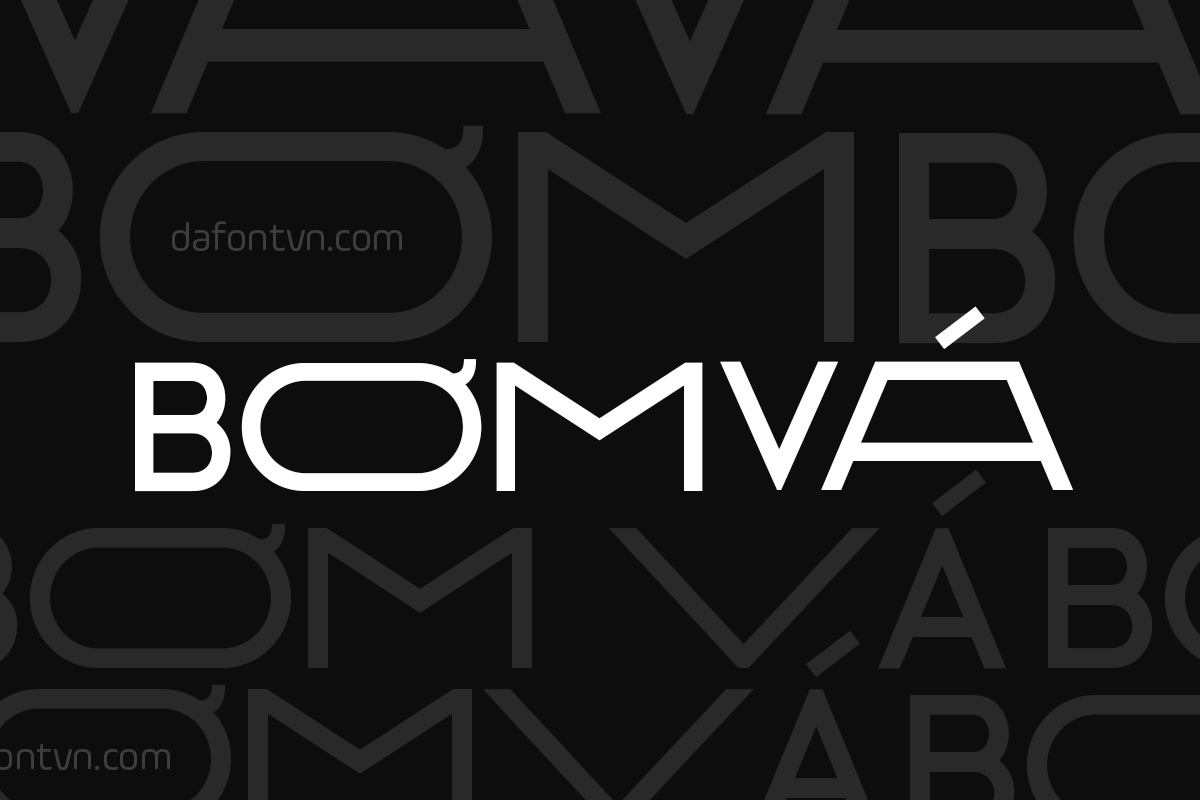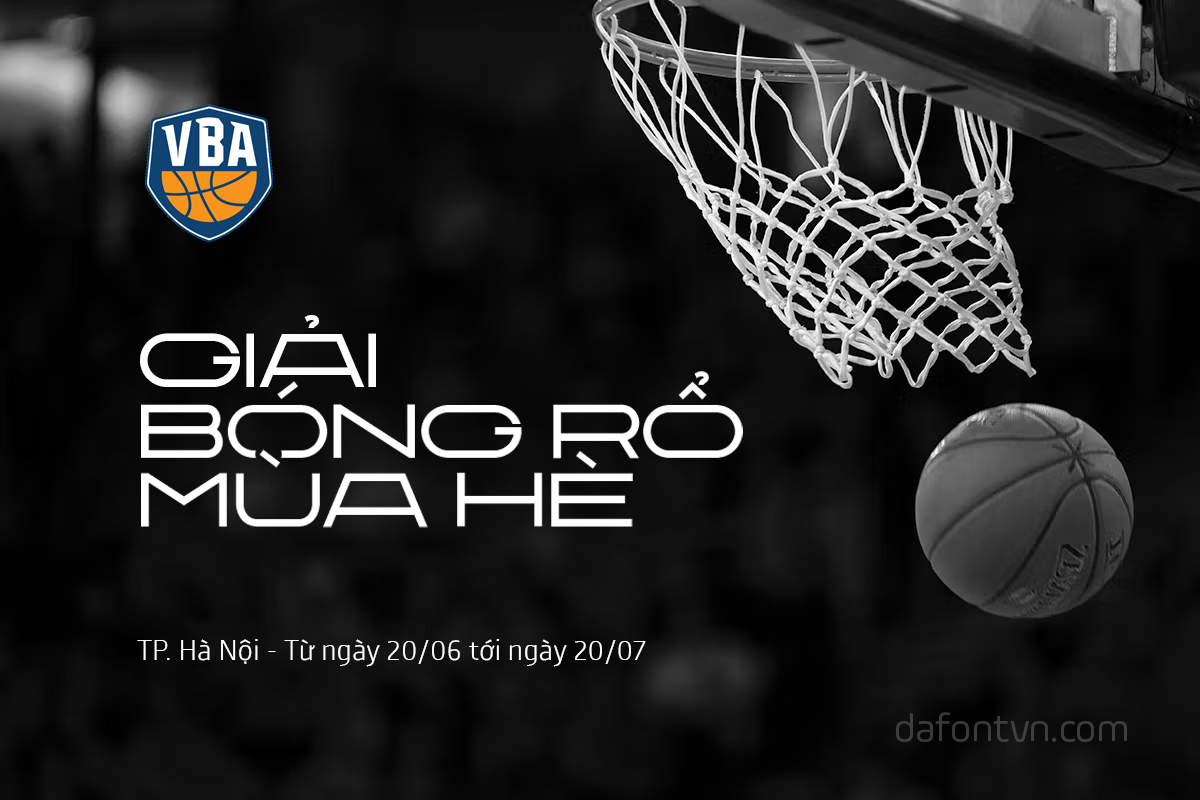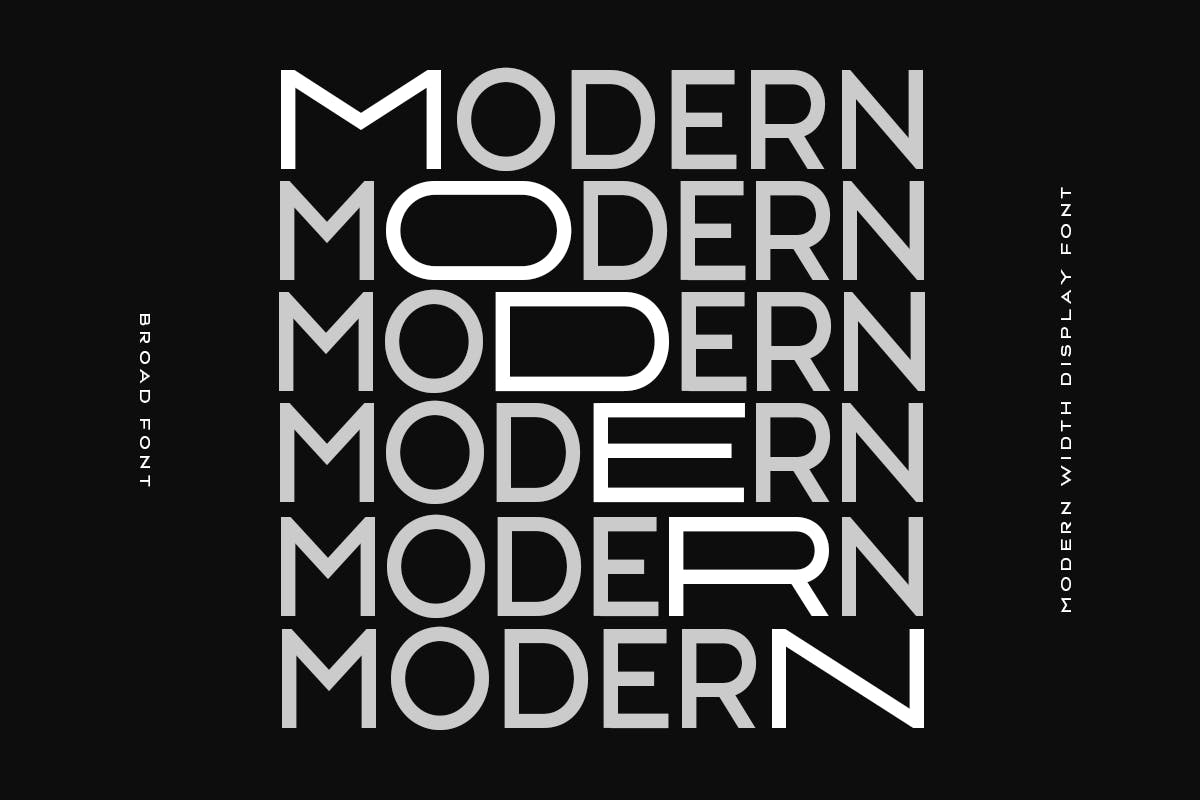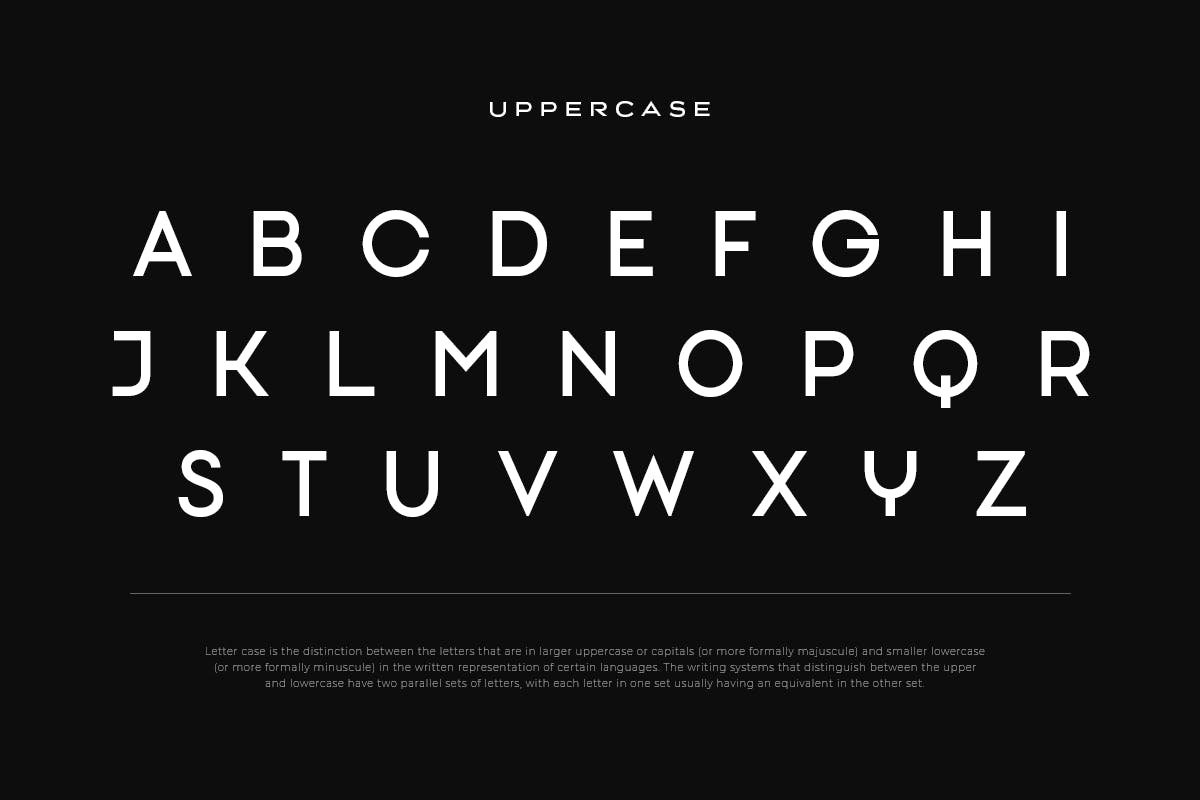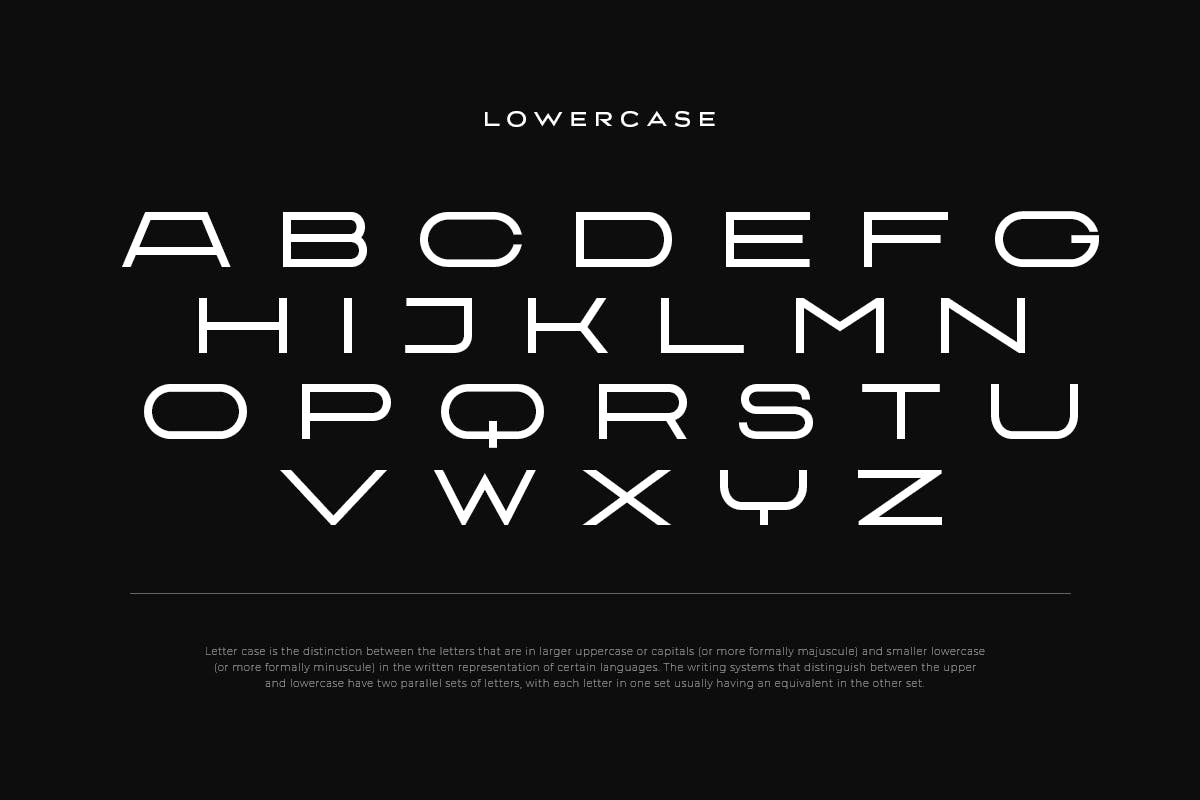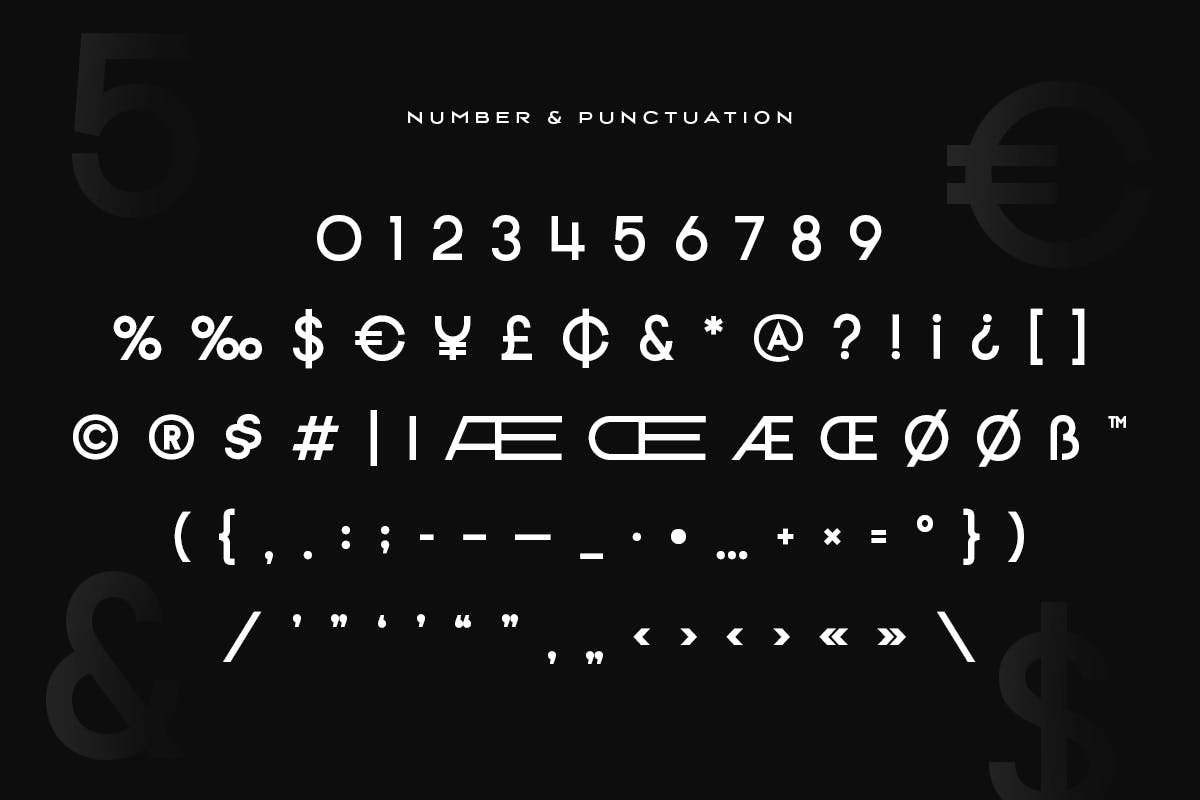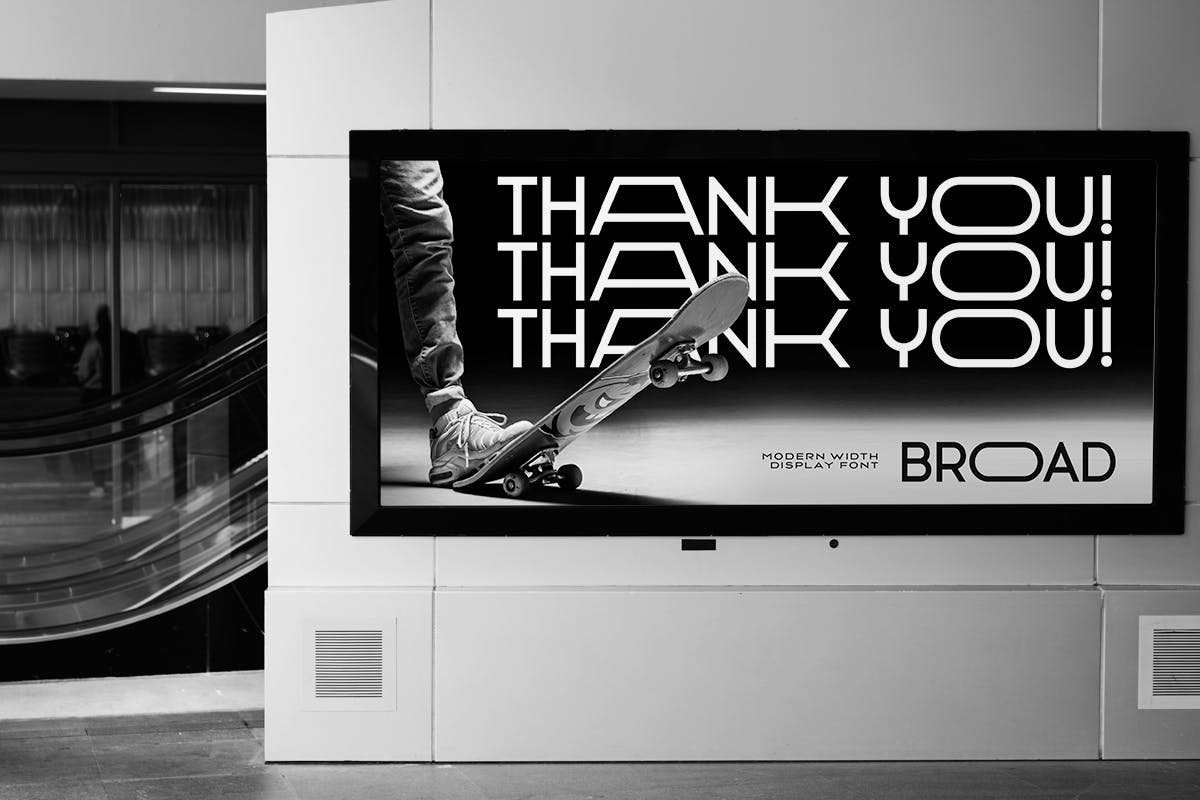
Font Việt Hóa Broad – Phông chữ rộng hiện đại
Font Việt Hóa Broad là một phông chữ Sans Serif với thiết kế độ rộng của từng chữ hiện đại hoàn hảo để sử dụng cho văn bản hiển thị, bạn có tận dụng kiểu chữ này cho các thiết kế sản phẩm, tiêu đề, banner quảng cáo, các text lớn…
BROAD – Modern Width Display Font – Font việt hóa đầy đủ, kerning, chỉnh sửa và tối ưu lại 1 chút so với font gốc.
BROAD - Modern Width Display Font
Font Việt Hóa Broad
Font BROAD - Modern Width Display Việt Hóa
BROAD - Modern Width Display Uppercase
BROAD - Modern Width Display Lowercase
BROAD - Modern Width Display Number & Punctuation
BROAD - Modern Width Display Font việt hóa